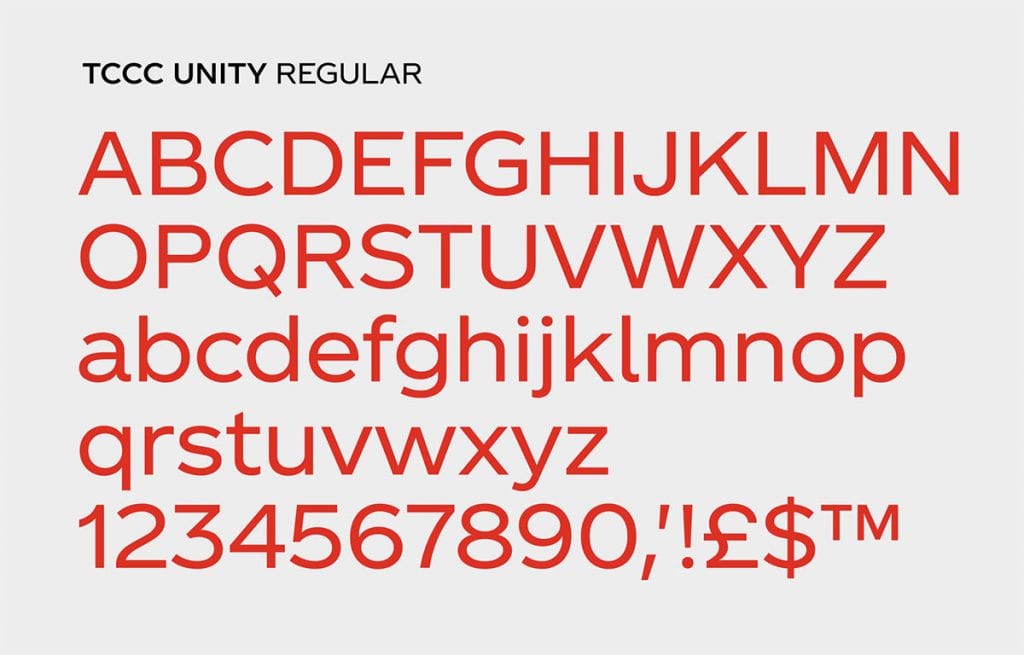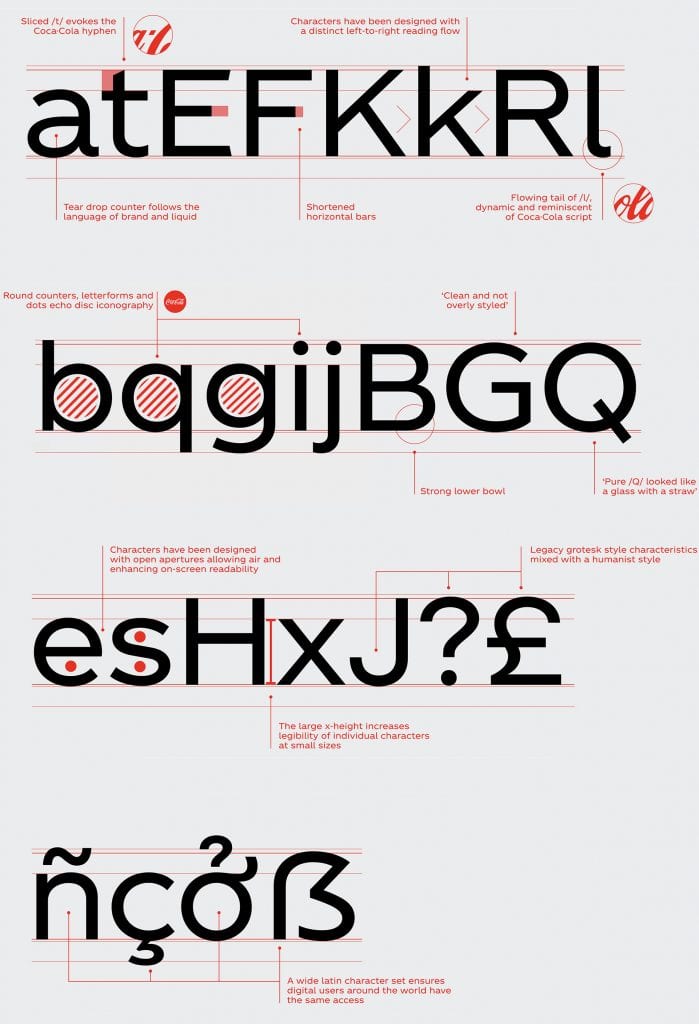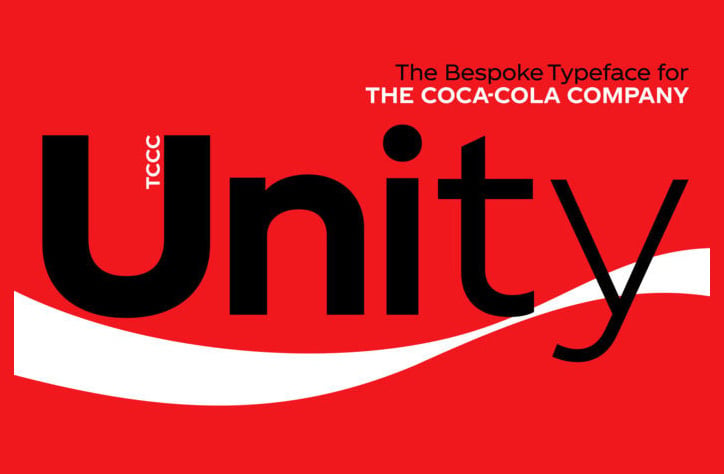
TCCC Unity, la nueva tipografía personalizada de Coca-Cola
Con el fin de facilitar su comunicación, Coca-Cola apuesta por el diseño propio y por hacer crecer su identidad visual.
El pasado 5 de enero, la marca de bebidas Coca-Cola ha revelado su nueva tipografía personalizada bajo el nombre de TCCC Unity, inspirada en una herencia modernista.
La tipografía fue realizada por Brody Associates junto con el equipo creativo de Coca-Cola. El nombre TCCC Unity, vienen del acrónimo de The Coca-Cola Company.
Con el fin de facilitar su comunicación, Coca-Cola apuesta por el diseño propio y por hacer crecer su identidad visual.
La nueva tipografía se caracteriza por la simpleza de sus formas, inspiradas en “el estilo geométrico y en los trazos circulares propios de las tipografías latinas”. Para su creación se ha considerado las clásicas curvas de su logotipo que se han traducido en glifos.
El vicepresidente creativo de Coca-Cola, James Sommerville comenta respecto a la tipografía que “encapsula el pasado de Coca-Cola y la tradición del modernismo americano”
Cabe destacar que esta tipografía ha sido creada para los entornos online u offline.